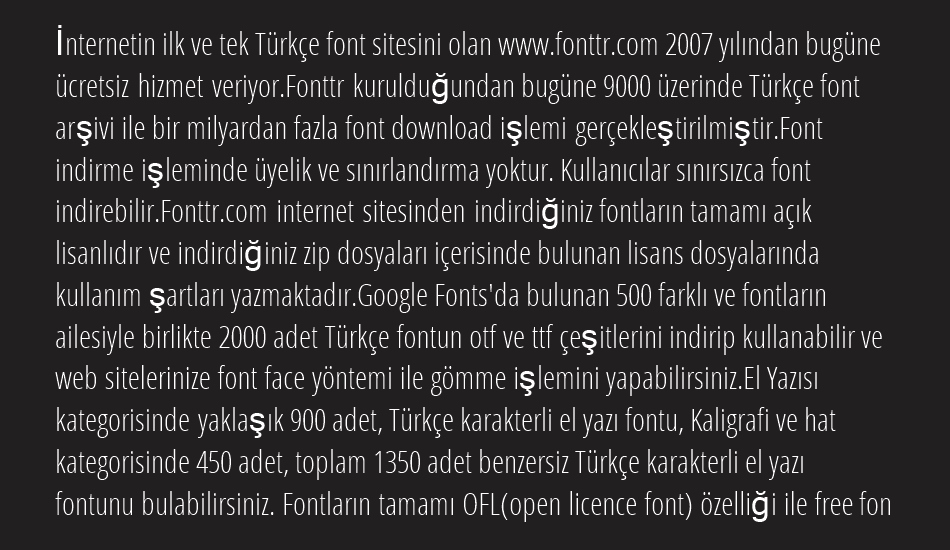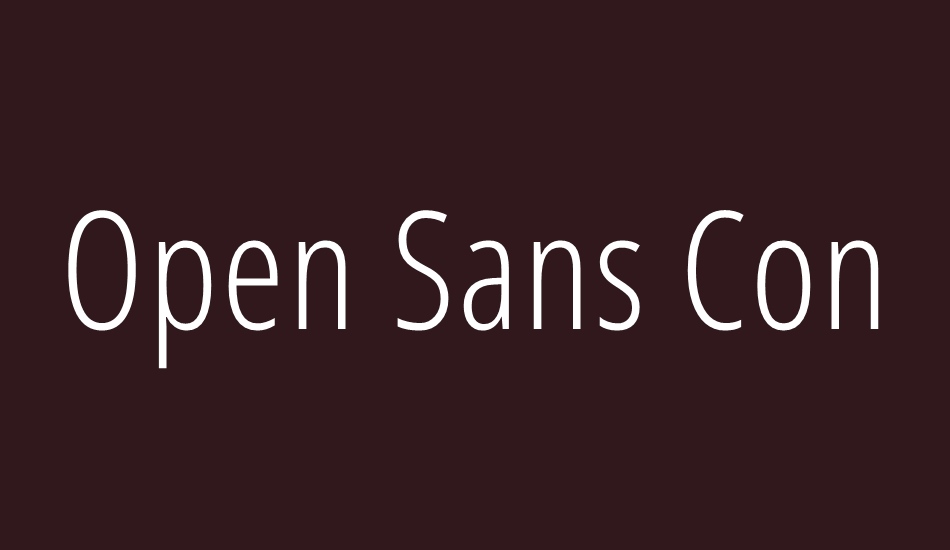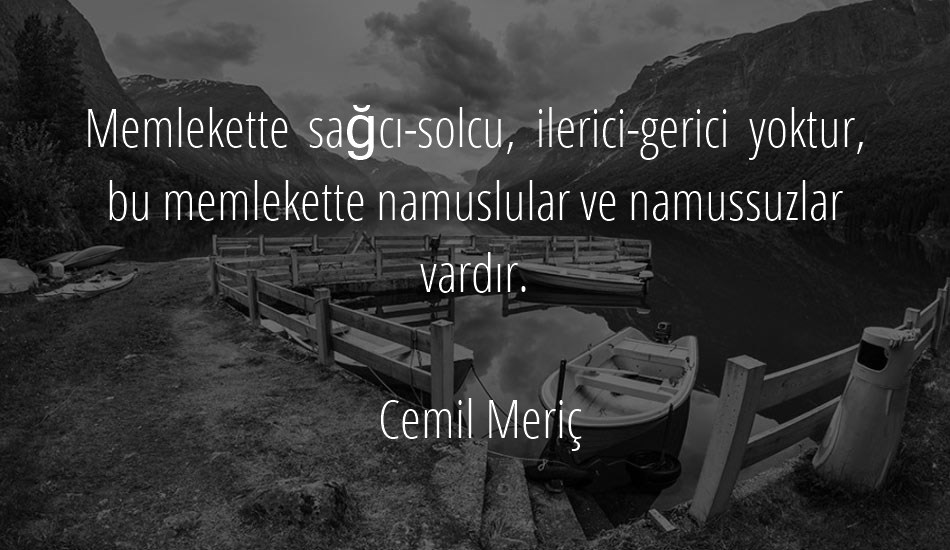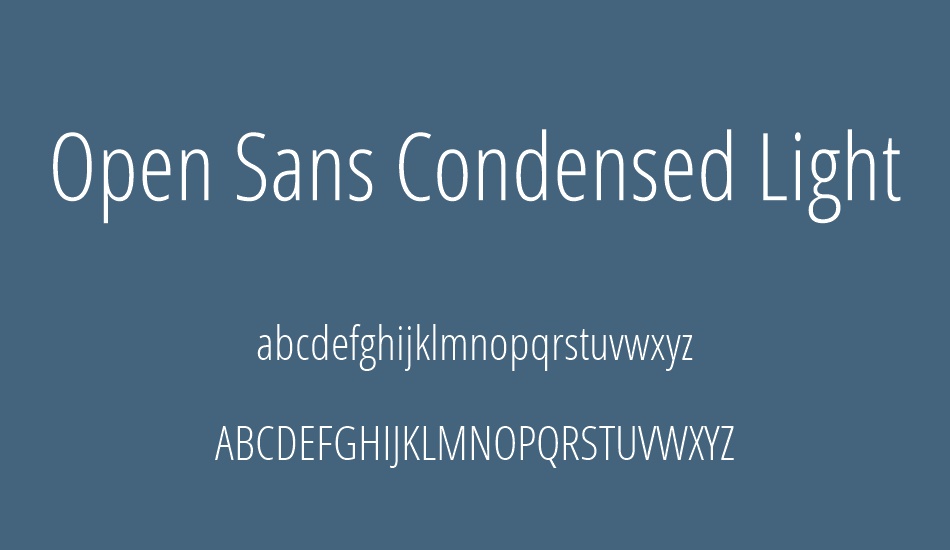
Open Sans Condensed font
Open Sans Condensed, Ascender Corp Tür Direktörü Steve Matteson tarafından tasarlanan bir hümanist sans serif yazı biçimidir. Bu sürüm, standart ISO Latin 1, Latin CE, Yunanca ve Kiril karakter setlerini içeren 897 karakter kümesini içerir. Open Sans Condensed font dik duruş, açık formlar ve nötr ancak samimi bir görünüm ile tasarlandı. Baskı, web ve mobil arayüzler için optimize edilmiş ve harf formlarında mükemmel okunabilirlik özellikleri taşıyor.
Open Sans Condensed Light font